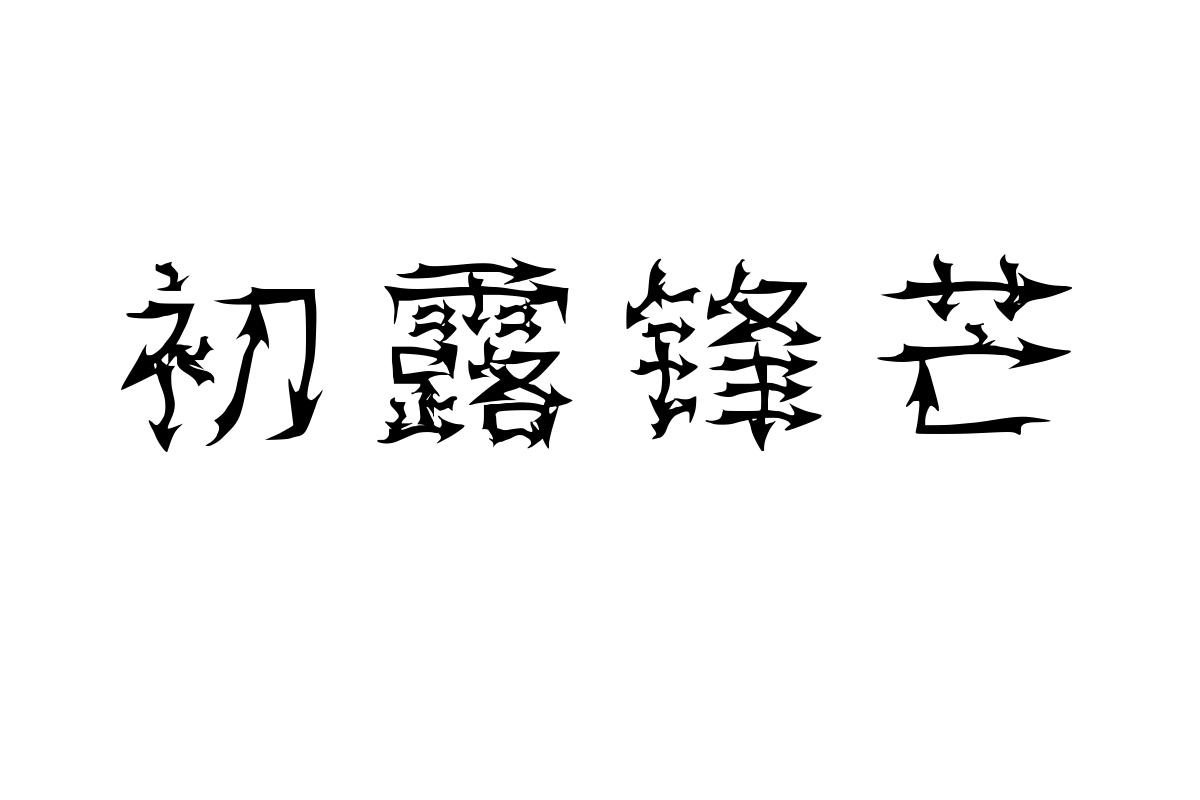
汉标箭头飘带体是一种具有独特风格的汉字字体,其特点是笔画流畅、结构紧凑、线条优美。这种字体适合用于设计广告、海报、宣传册等需要突出视觉效果的场合。
特点:
1. 笔画流畅:汉标箭头飘带体的笔画呈现出一种流畅的感觉,使得整个字体看起来更加美观。
2. 结构紧凑:该字体的结构紧凑,每个字的笔画都紧密相连,使得整体看起来更加协调。
3. 线条优美:汉标箭头飘带体的线条优美,给人以视觉上的享受。
4. 适应性强:这种字体适用于各种类型的文本,如标题、正文、注释等。
适用场景:
1. 广告设计:汉标箭头飘带体适合用于广告设计,可以有效地吸引观众的注意力。
2. 海报设计:该字体适合用于海报设计,可以增加海报的趣味性和吸引力。
3. 宣传册设计:汉标箭头飘带体适合用于宣传册设计,可以增强宣传效果。
4. 网站设计:该字体适合用于网站设计,可以提升网站的品牌形象。